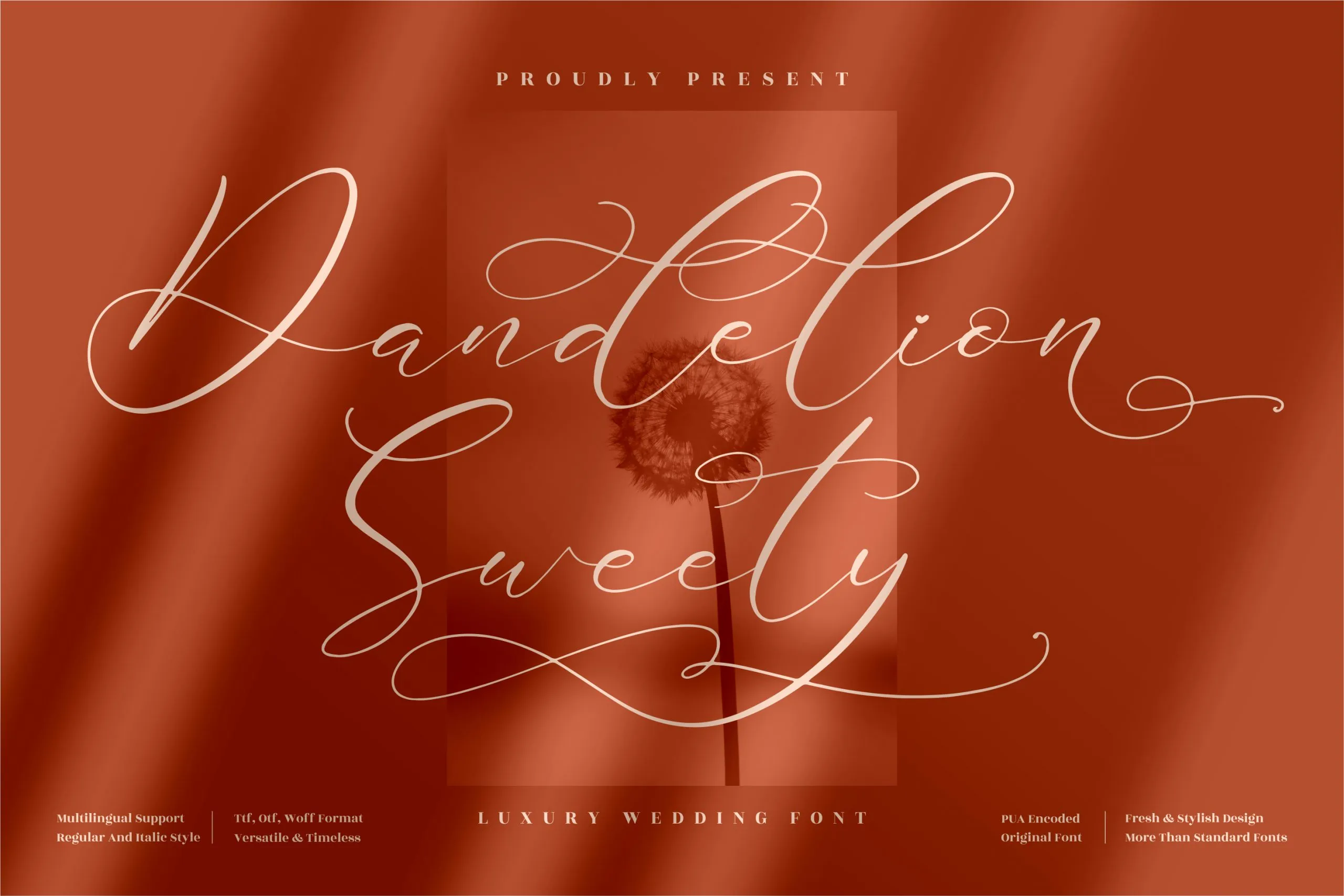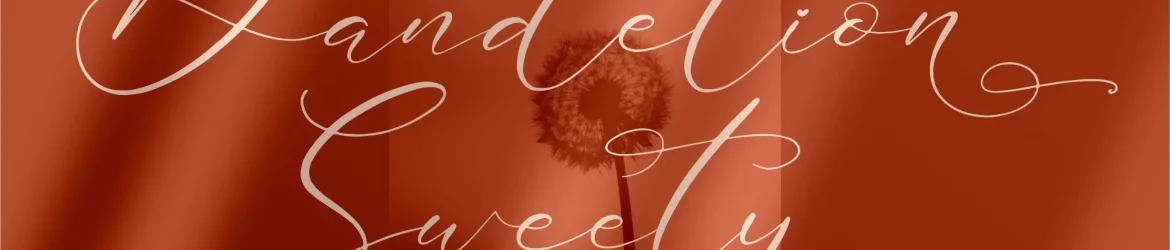
Dandelion Sweety Font – Download Grátis
A Dandelion Sweety Font é uma elegante tipografia de script criada pelo estúdio Perspectype Studio, perfeita para projetos que exigem um toque romântico e delicado. Esta fonte se destaca não apenas por seu encantador design, mas também pela sua versatilidade. Ideal para diversos tipos de criação gráfica, como logotipos, projetos de marca, designs para mobiliário, embalagens de produtos, mug decorativo e até mesmo impressões digitais em cartazes ou tags, a Dandelion Sweety Font se destaca também como uma excelente escolha para anúncios personalizados, selinhos de convite, carteirinhas de visita, capas de livros e outros projetos que buscam um ar delicado. Com sua beleza única e sua capacidade de transformar qualquer projeto em algo especial, a Dandelion Sweety Font se torna um acessório indispensável para designers e criadores de conteúdo gráficos no Brasil.